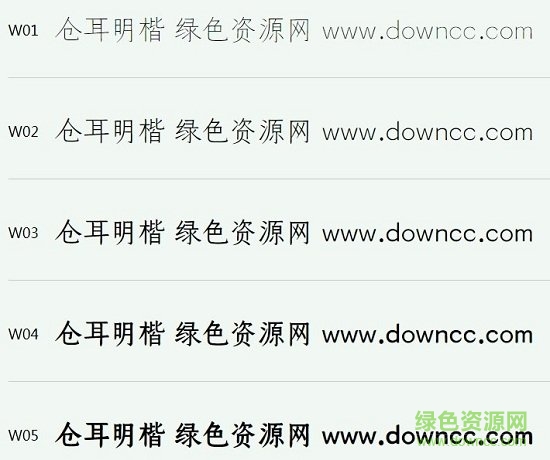
倉耳明楷體包含了w03、w01、w02、w04、w05等五個字重,是一款清麗溫婉的楷書字體,結(jié)構(gòu)緊湊卻不強硬,給人輕松閱讀、如沐春風的悠閑體驗,快來綠色資源網(wǎng)搶先嘗試吧!
倉耳明楷是一套創(chuàng)新性的家族字庫,設(shè)計師創(chuàng)造性的將明代宋體高挑緊湊的結(jié)構(gòu)和新穎的楷體筆形相結(jié)合,創(chuàng)造出具有全新視覺風格的字體,更易識別,美觀與實用兼?zhèn)洹?/p>
倉耳明楷家族字體,蟲戈劍雨千變?nèi)f化,結(jié)體布局間長短交縱,閱讀時回味無窮!